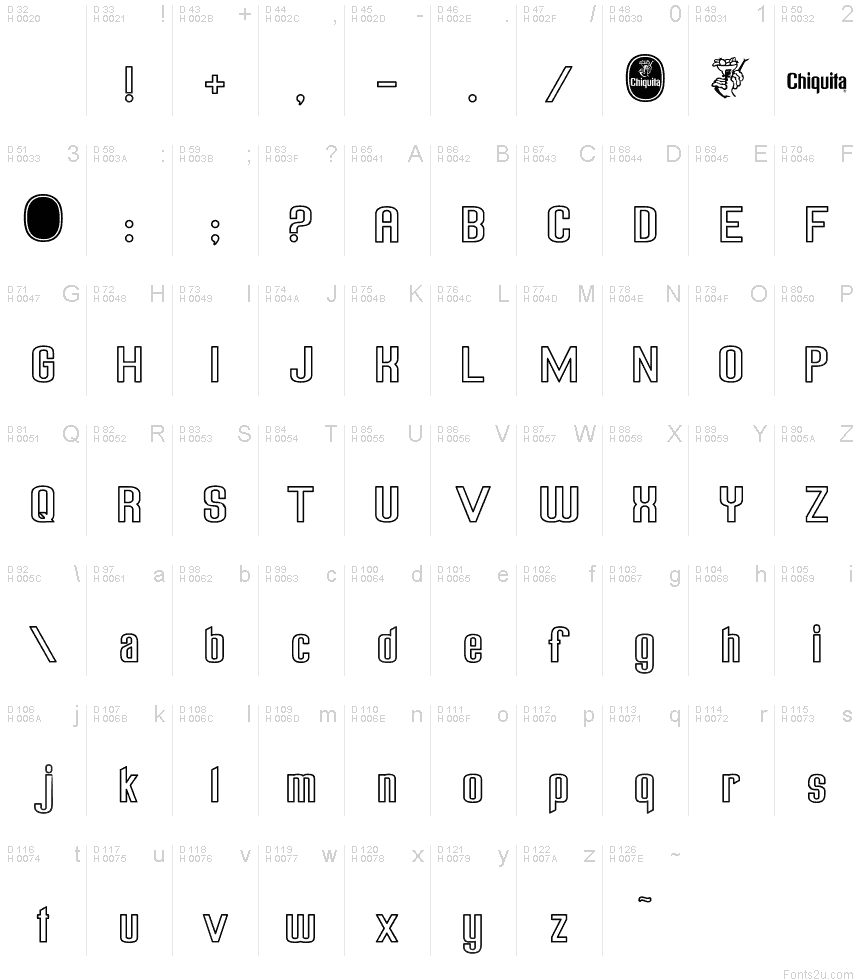
Chiquita Outlined di Samuel Park è un carattere display moderno e gratuito con uno stile contornato. I suoi tratti vuoti, simili a tubi, e i bordi dolcemente arrotondati conferiscono alle lettere un aspetto leggero e vivace, mentre piccoli intagli o dettagli giocosi aggiungono carattere senza creare confusione. La struttura a doppia linea rende ogni parola ariosa e audace, catturando lo sguardo senza mai sembrare pesante o troppo fitta.
Con Chiquita Outlined, titoli e logotipi acquistano la nitidezza tipica delle insegne al neon, perfetta per poster, packaging, flyer, copertine di album, branding di eventi e grafiche per i social media. Questo font gratuito dà il meglio di sé nelle dimensioni più grandi, dove le forme contornate rimangono pulite e leggibili. Per un layout equilibrato, abbinalo a un carattere sans serif geometrico semplice o a un font di sistema per il corpo del testo.